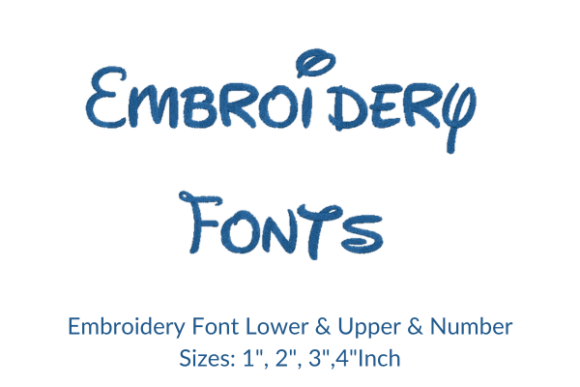
Embroidery Fonts Design
Het vinden van de juiste ontwerpelementen kan lastig zijn, maar Embroidery Fonts Design biedt een uitzonderlijke collectie die uw werk direct naar een hoger niveau tilt.